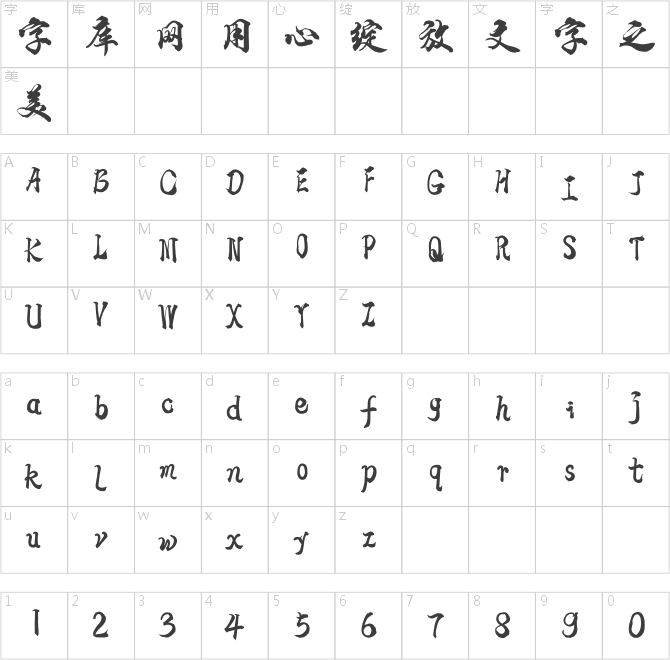
段宁毛笔行艺体 详情页
字体名称: 段宁毛笔行艺体
段宁毛笔行艺体含9663个汉字和必备的其他字符,由书法家段宁老师手写原稿并亲自制作完成的一套字库,是一套真正的汉字大字库。有简体字、繁体字、生僻字,你所要的字这里都有。这套字最大的亮点是,字体气势磅礴,遒劲有力,有汉字的规范结体又有艺术的元素,同时还保留了毛笔的飞白和游丝,基本上与毛笔写在宣纸上一样的效果。这款大字库适合影视、网页、包装、印刷等各类广告媒体使用。 非商用免费,商用必须联系版权人段宁购买授权,电话/微信 15851552102